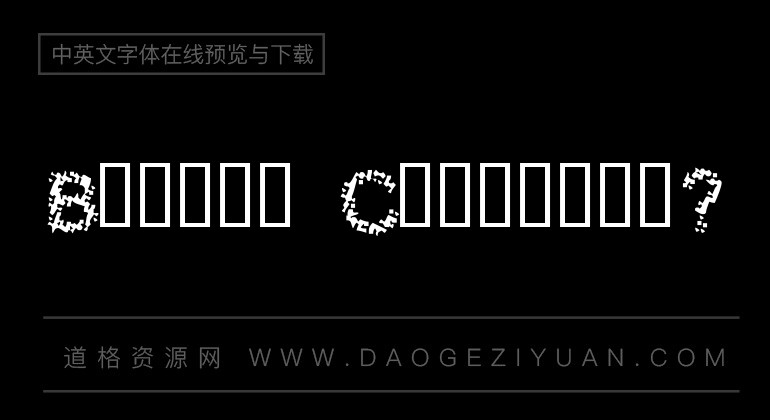
很抱歉,我认为您可能想查询的是“Bloody Crapnel”字体。 Bloody Crapnel是一种免费的英文字体,它采用了一个血腥和颓废的设计风格。这种字体的字母形状中带有刺骨的棱角和撕裂的边缘,看起来很有力量和威慑力。它通常被用来突出一些血腥、惊悚、或者暴力的主题,比如恐怖电影、游戏、或者摇滚乐队的专辑封面等。该字体支持英文大写字母和数字,可以在Windows和Mac操作系统上使用。内容介绍
Bloody Chrapnel?是一款非常不错的手写艺术字体,具有很好的视觉感,适合于文化类的宣传设计、商业类品牌的广告和产品包装设计以及个性化文字排版等较多场景。